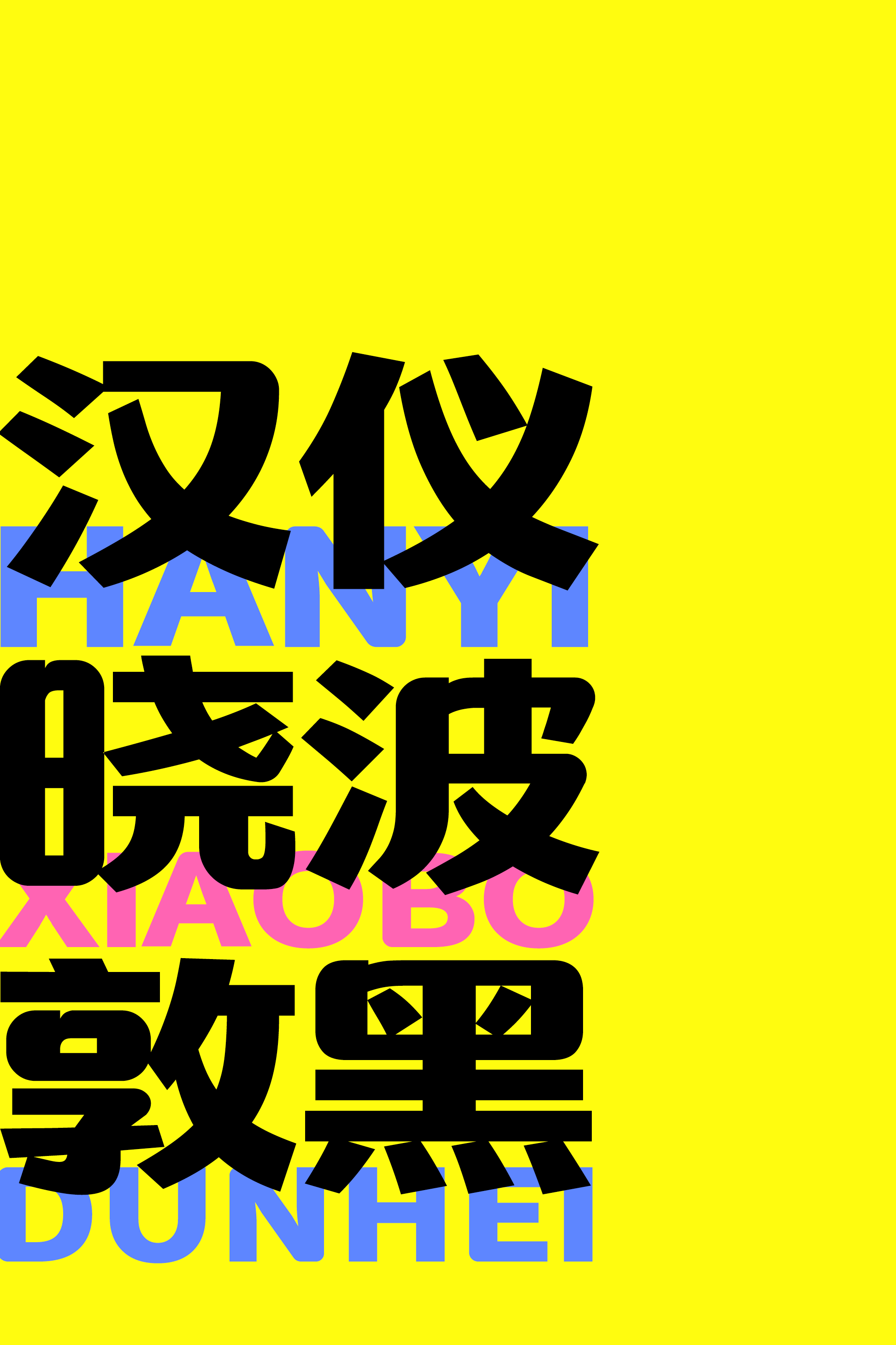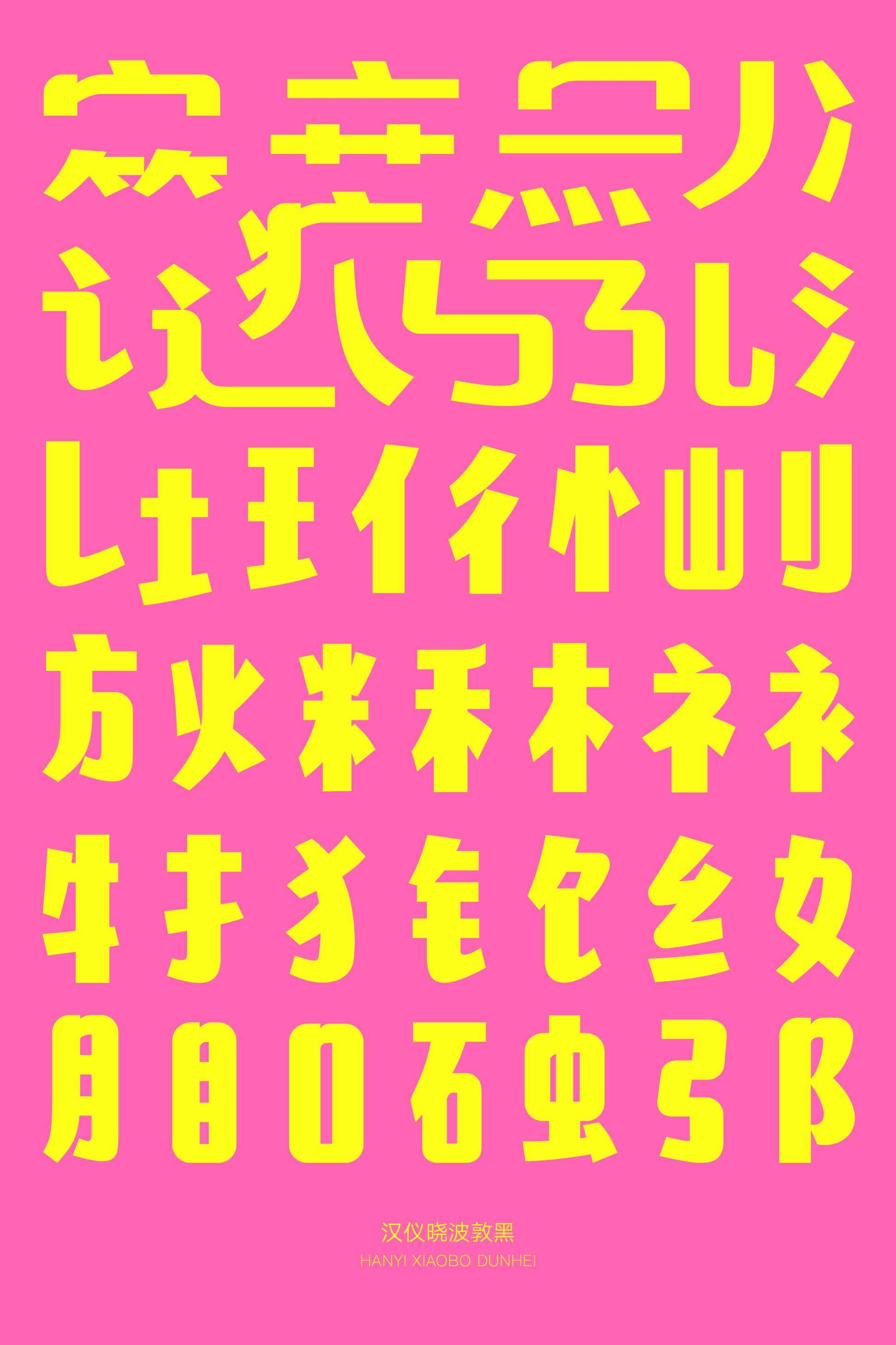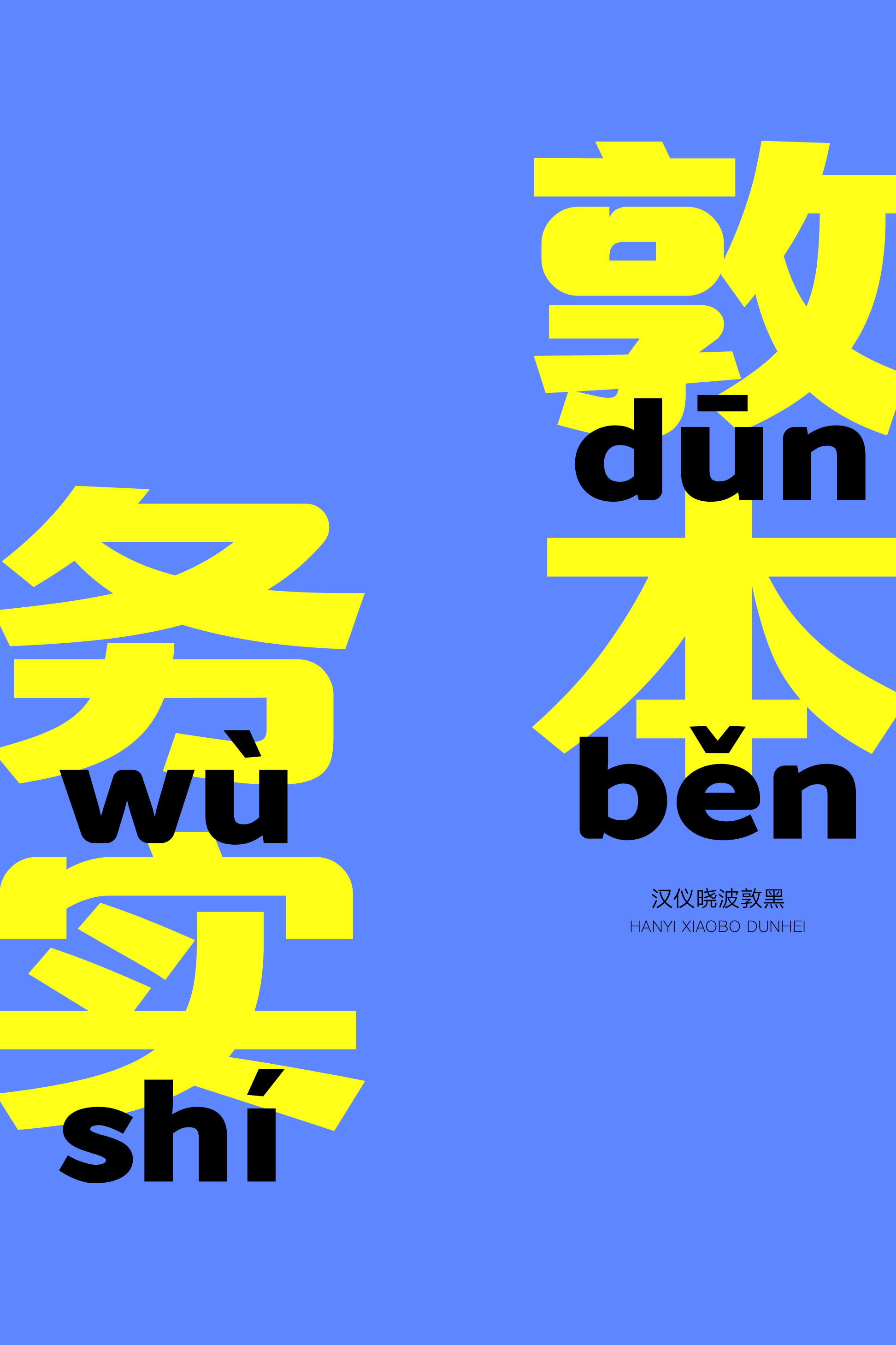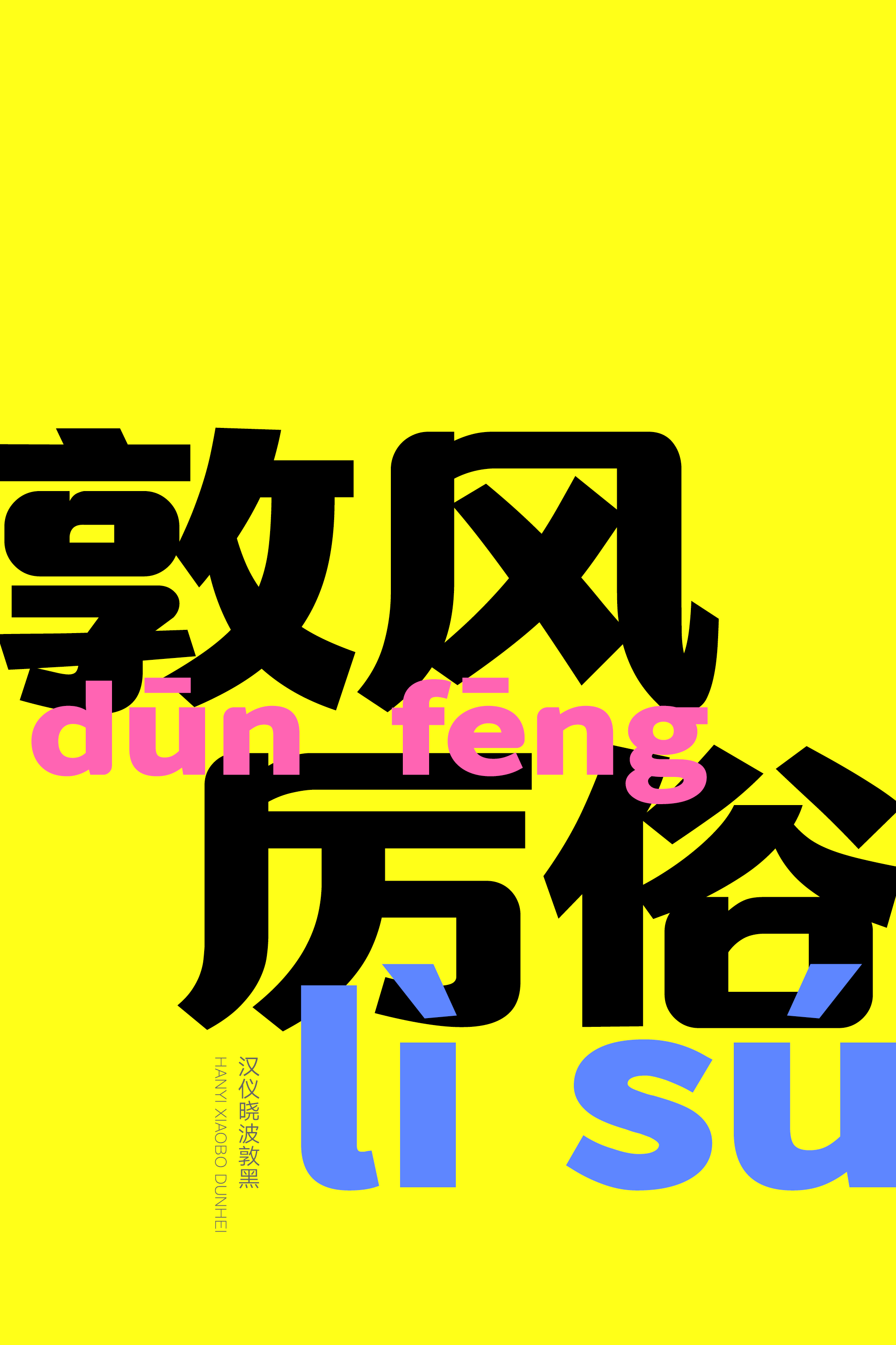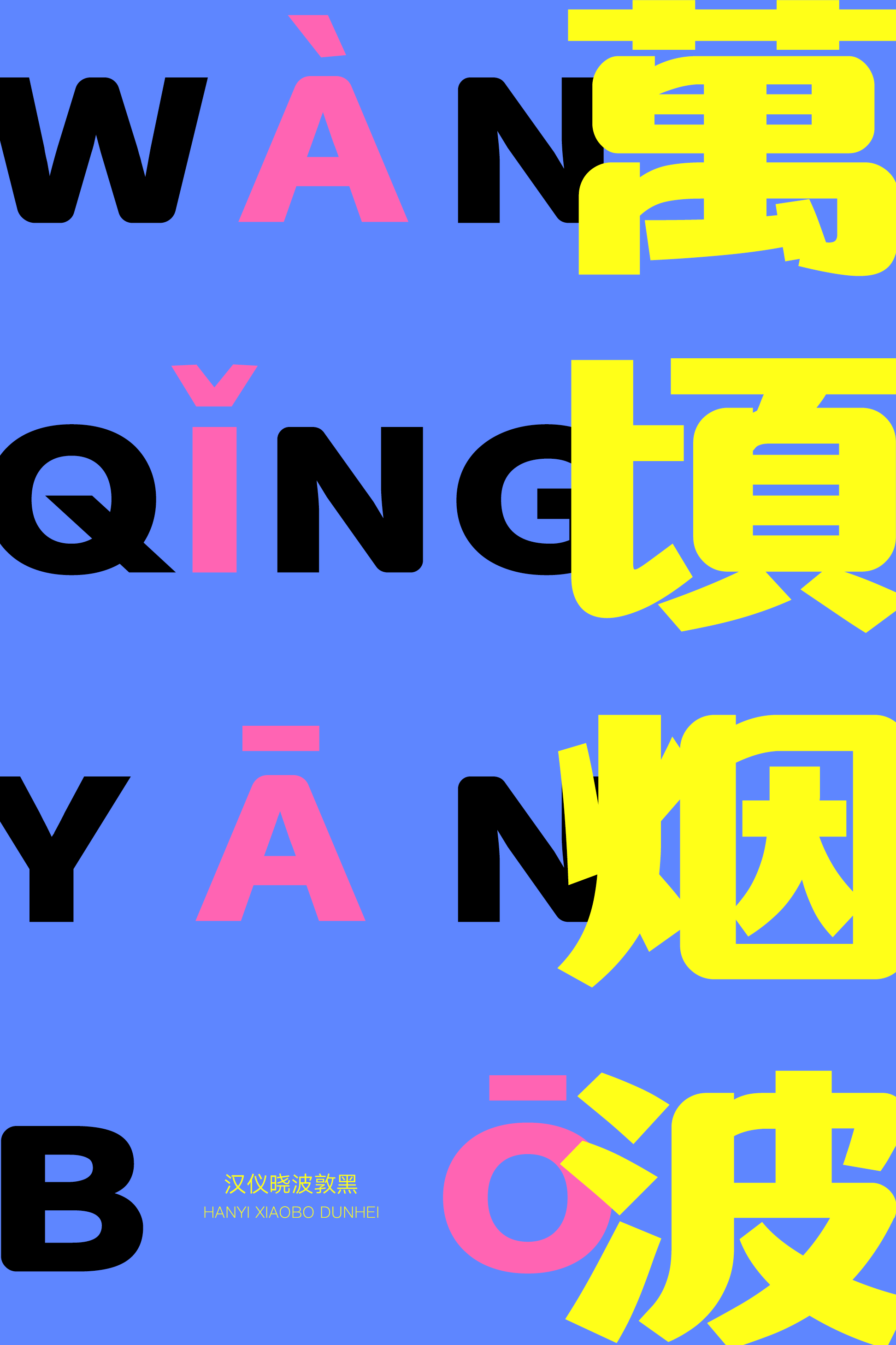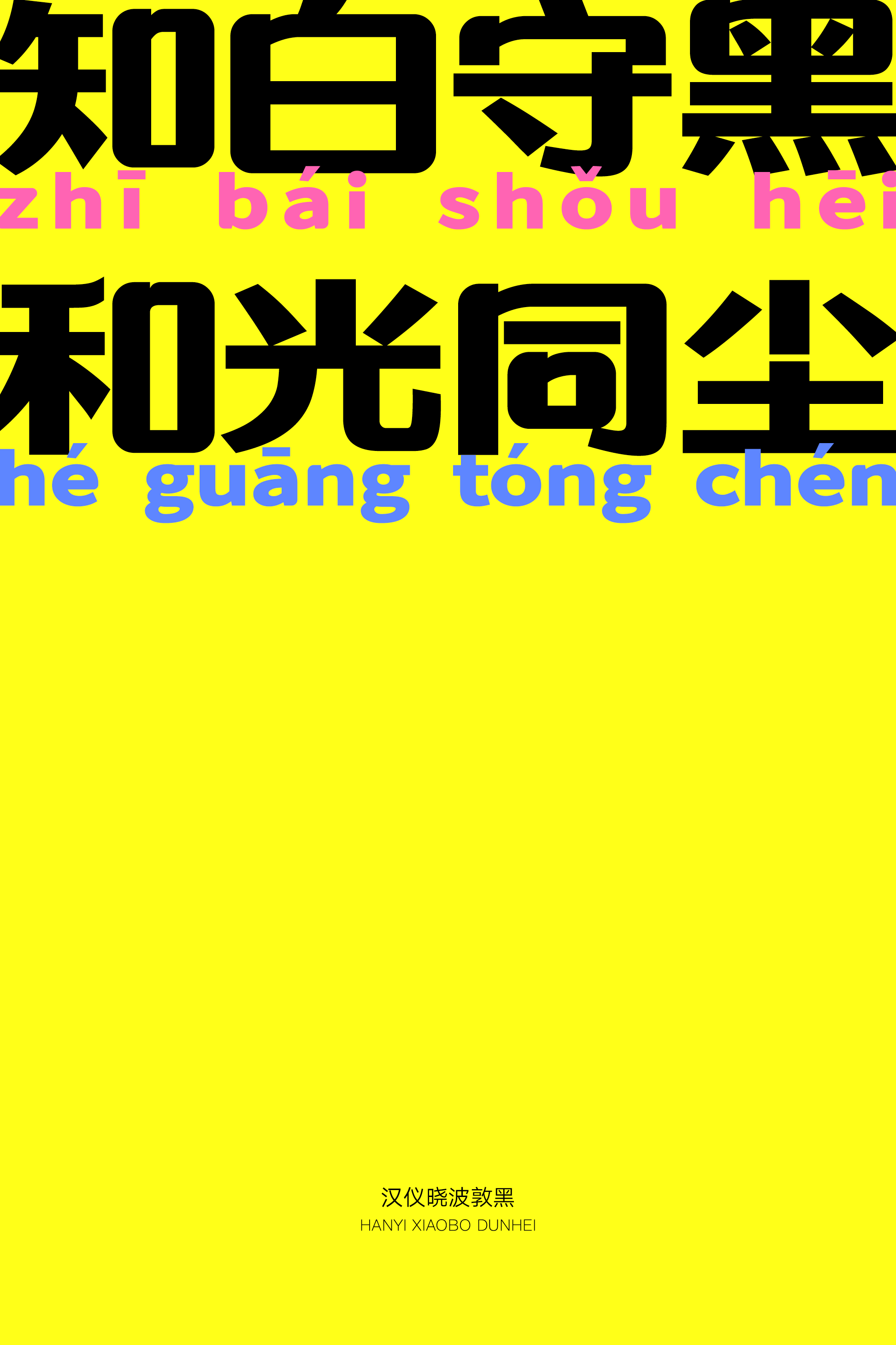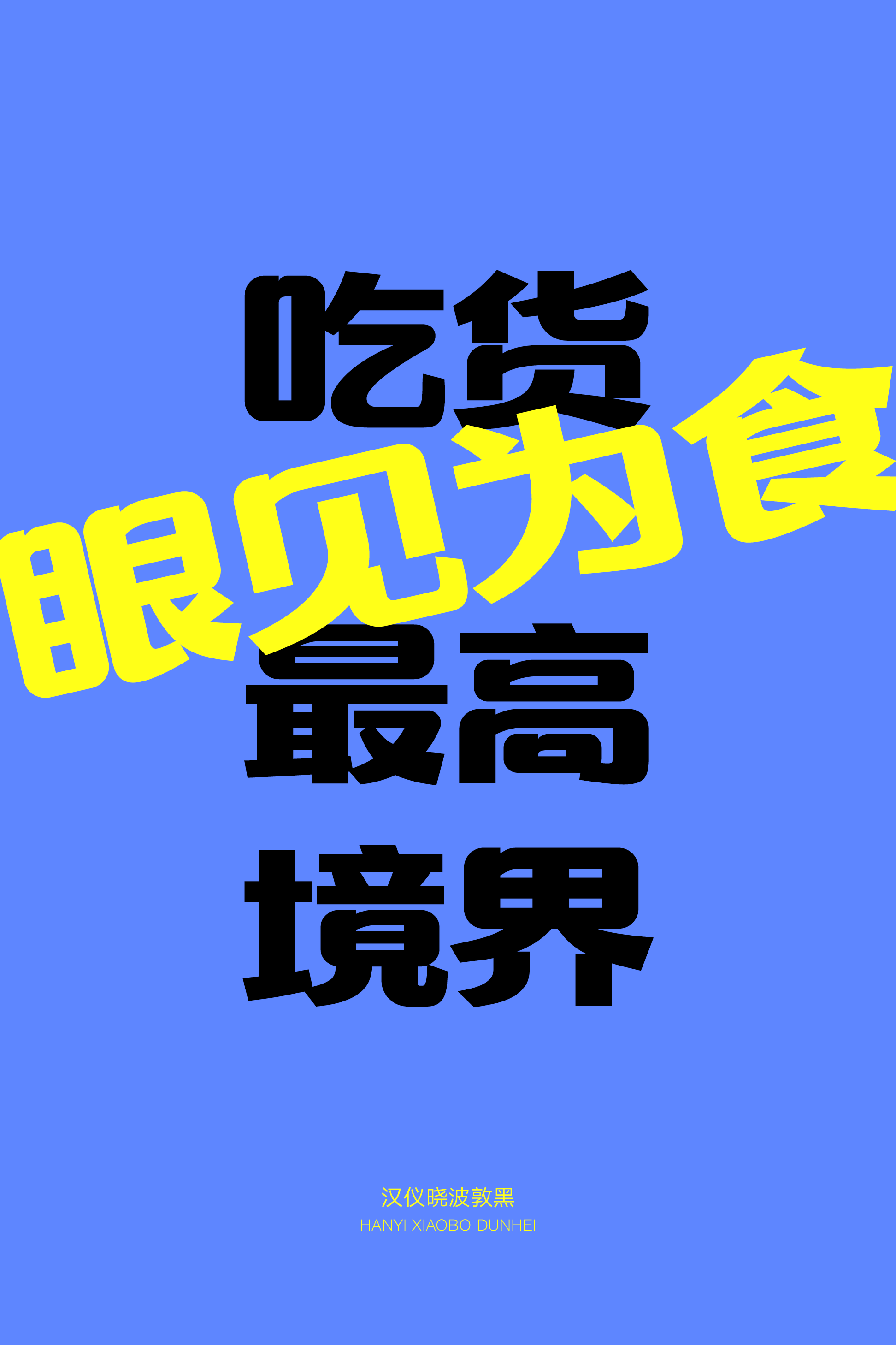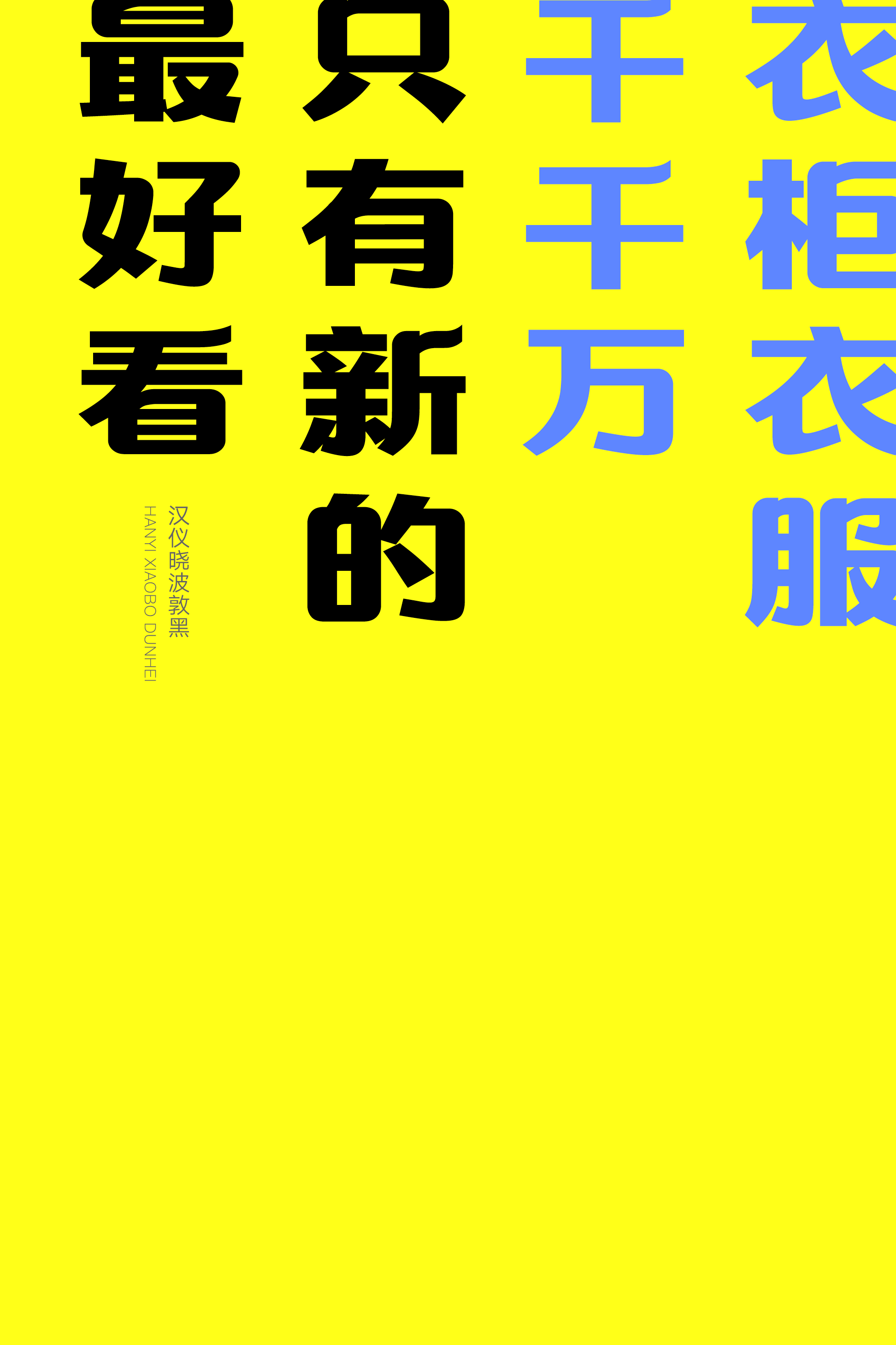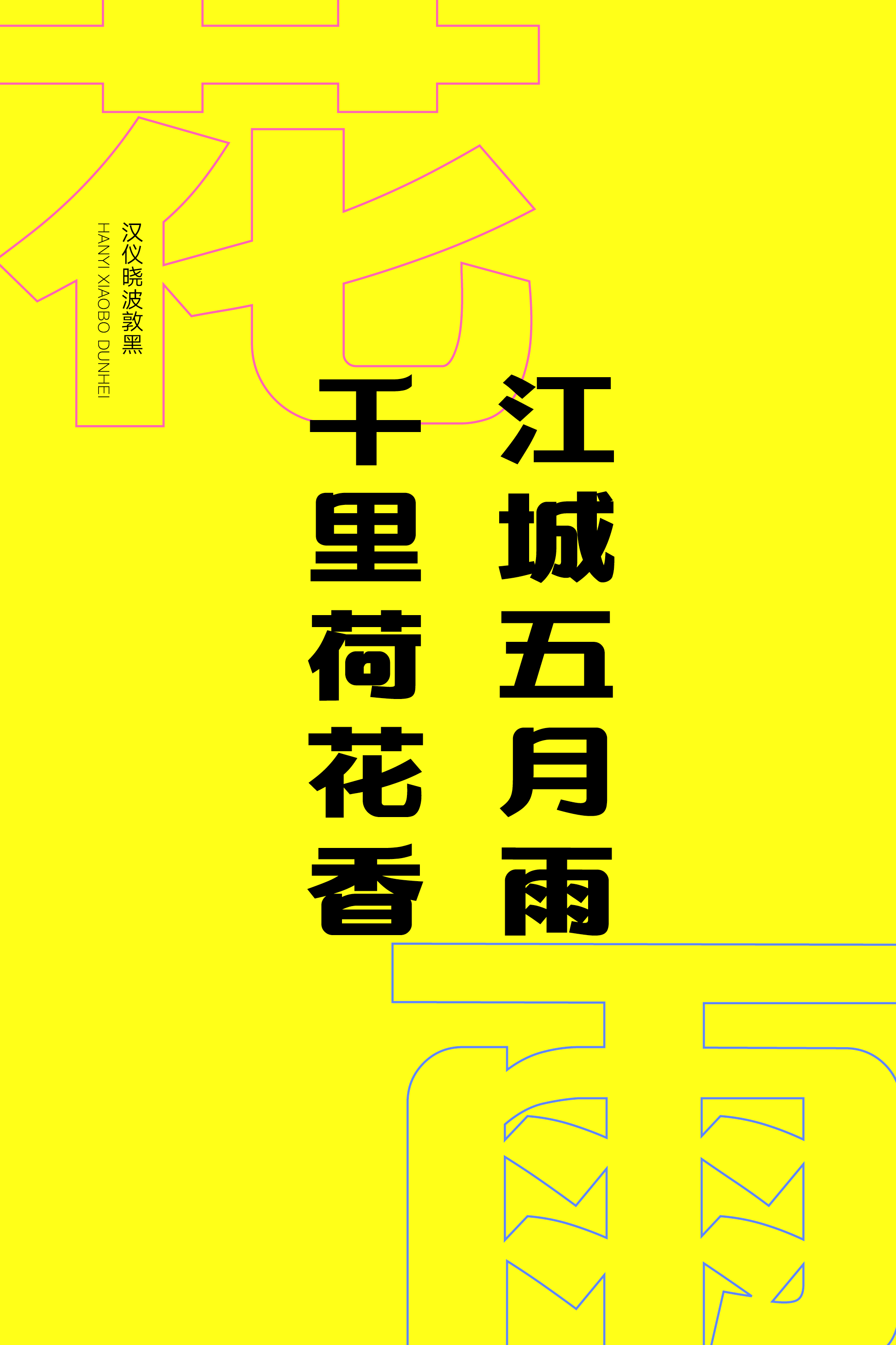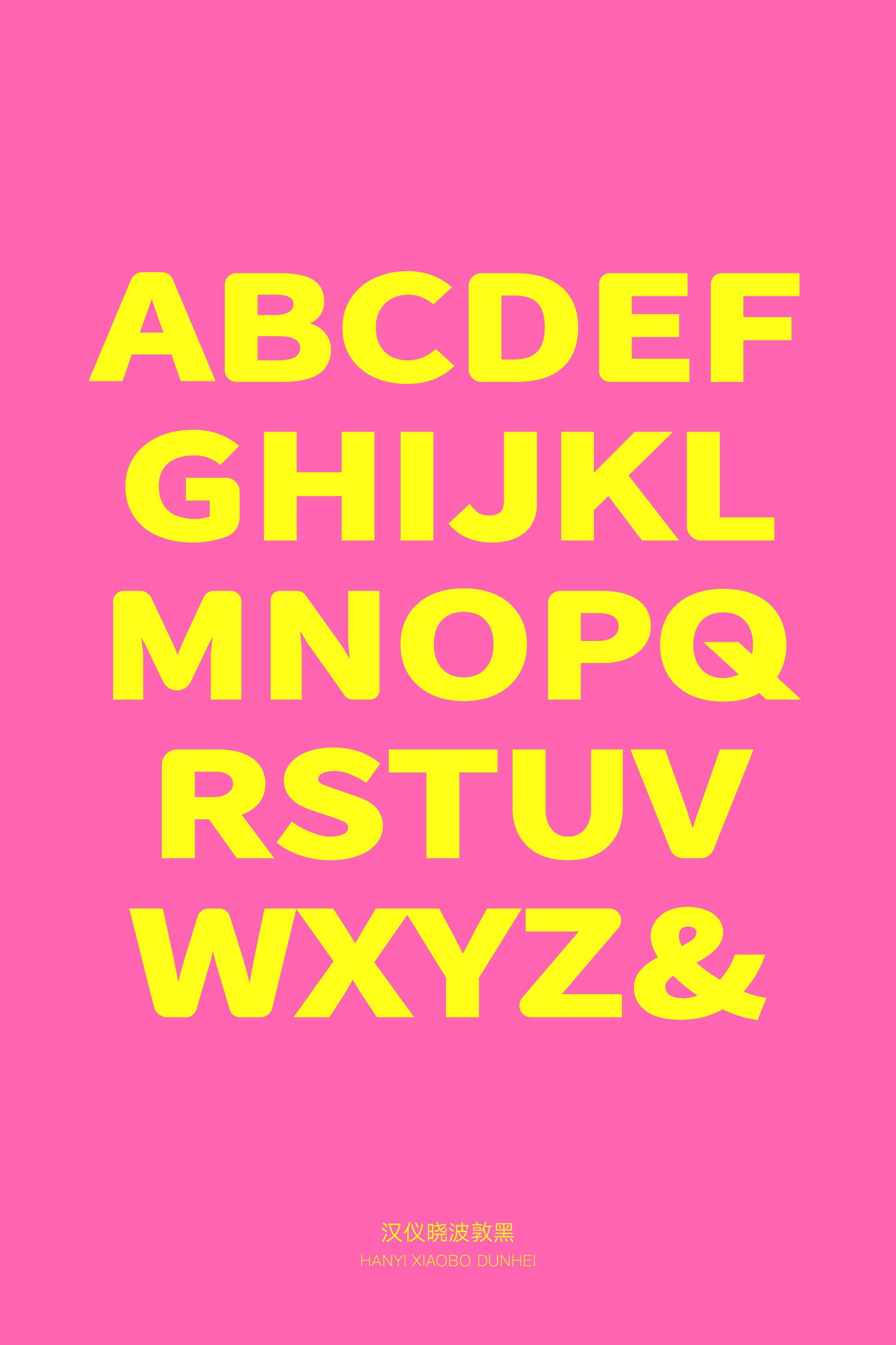
汉仪晓波敦黑
扁宽饱满的字形和敦实简约的笔画相加,等于简约有趣的汉仪晓波敦黑!外圆内方的设计让这款字体的视觉感受既有厚实的重量又不失亲和力,适合用于标题和较短文本的排版,无论是休闲餐饮的品牌包装、影视娱乐的标题花字,还是游戏绘本中的文本应用,汉仪晓波敦黑都是可靠的选择。
字形扁宽饱满,是一款敦实的黑体。
外圆内方,视觉感受敦厚而充满亲和力。
横平竖直、横细竖粗;撇捺起笔细、收笔粗,形成友好的弧度。
西文部分保持了一致的扁宽造型和外圆内方的设计,中西文匹配和谐统一。